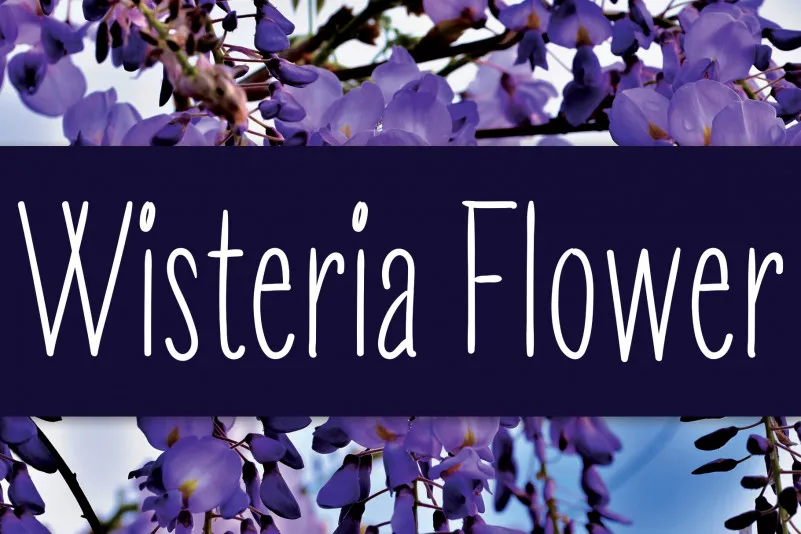
Wisteria Flower Handwritten Font é uma elegante e cuidadosamente escrita fonte que traz a essência delicada do traçado à sua arte digital. Esta fonte natural e única se destaca por seu charme suave, fazendo dela uma escolha perfeita para um grande variedade de projetos gráficos. Seja para o design de logotipo, rótulos ou qualquer outro tipo de conteúdo visual que exige um toque pessoal e delicado, Wisteria Flower Handwritten Font oferece a versatilidade necessária para se adaptar em vários contextos. Uma fonte ideal tanto para aqueles buscando uma paleta de cores suave quanto para quem deseja adicionar um elemento elegante ao seu trabalho gráfico.